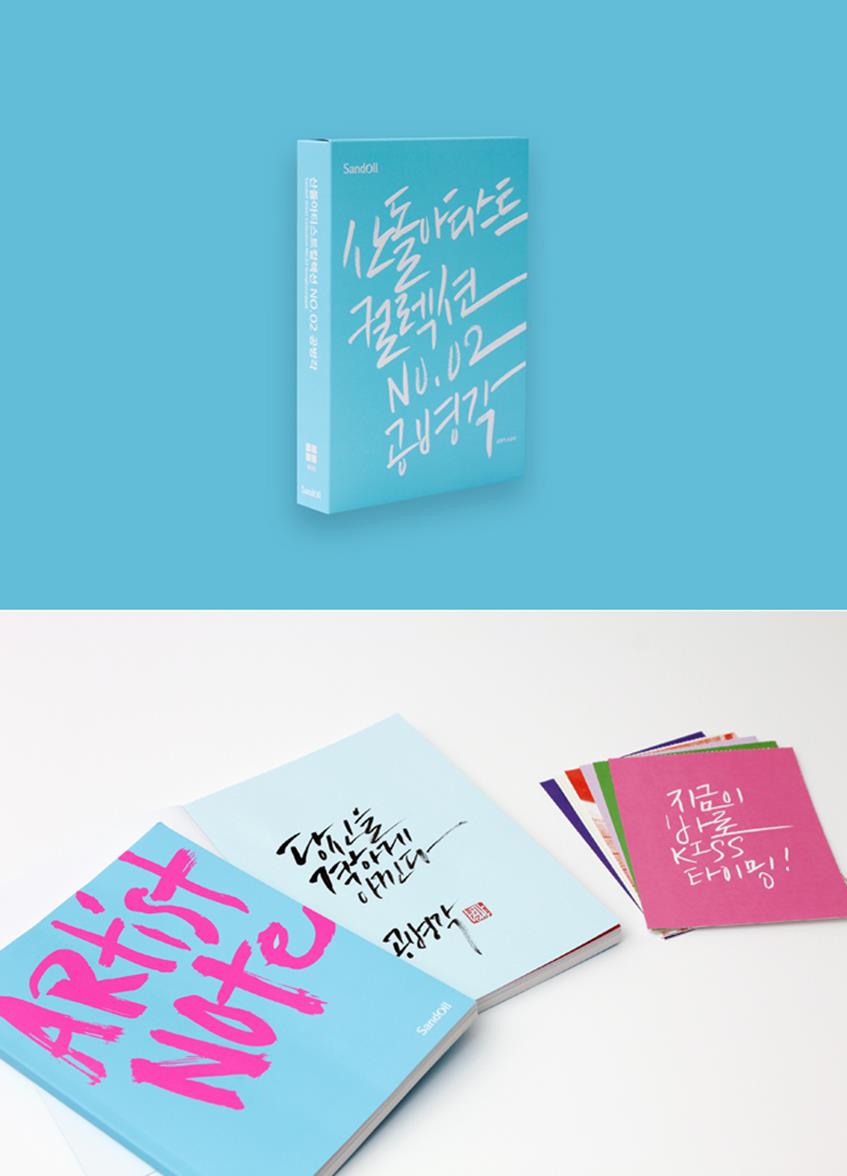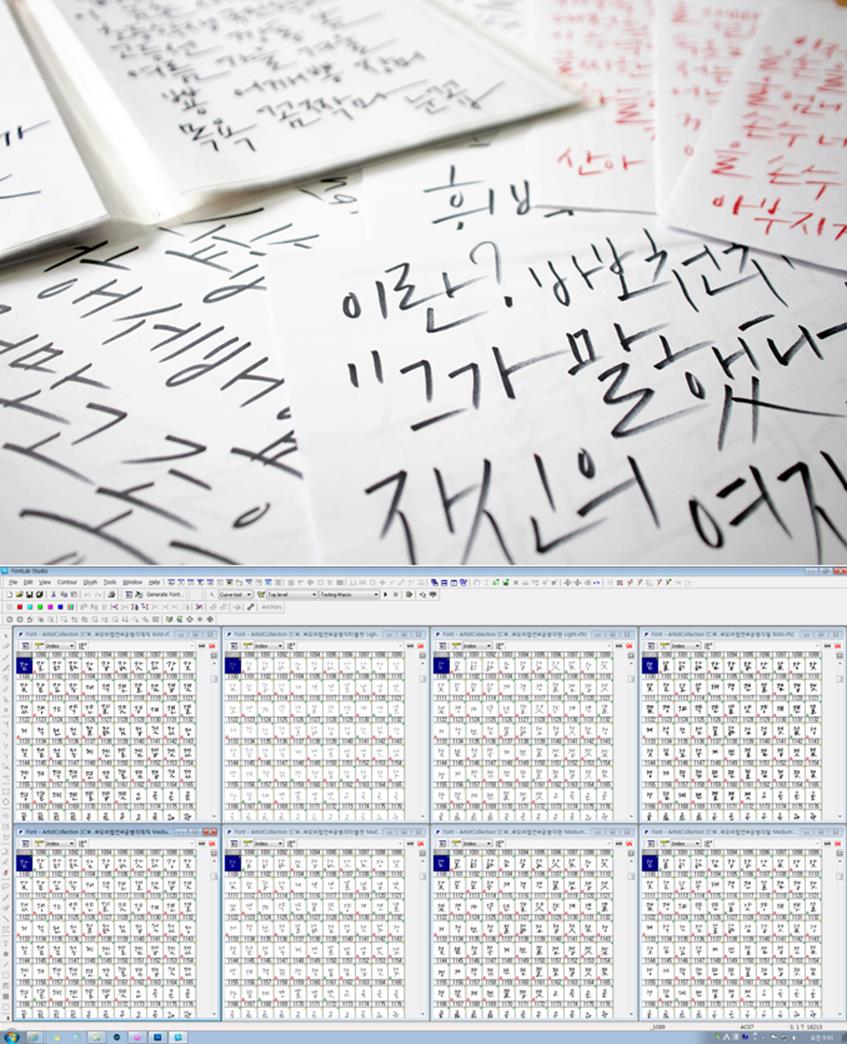
손이 행복해 삶이 즐거운 캘리그라퍼, 공병각
한 번 들으면 잊을 수 없는 이름. 한 번 보면 쉽게 잊을 수 없는 손글씨. 디자이너이자 크리에이티브 디렉터, 그리고 시선과 마음을 사로잡는 감성적 손글씨로 널리 알려진 캘리그래퍼 공병각을 만났다.
작가님 근황은 어떠신가요? 연초에 책 한 권을 내시고 6월 말에 또 한 권을 마무리하셨는데요.
네. 안녕하세요. 공병각입니다. 말씀대로 올해 2월에는 다섯 번째 에세이 <어떻게 사랑이 그래요>를 마무리해서 선보였고, 6월 말에는 제 첫 번째 손글씨 실용서라고 할 수 있는 <손글씨 잘 써서 좋겠다>를 출간했습니다. <손글씨 잘 써서 좋겠다>는 제가 작업했던 앨범 디자인과 기업 콜라보레이션 상품 작업 과정도 소개하고 제 경험과 노하우를 바탕으로 손글씨 쓰는 방법을 설명해주는 책이에요. 그동안 캘리그라피를 배우고 싶다는 문의와 어떻게 하면 손글씨를 잘 쓰는지 질문하는 분들이 굉장히 많았어요. 어떻게 하면 손글씨를 잘 쓰는지, 어떤 도구를 사용하면 좋은지 이제 답을 해줄 시점이 되었다는 생각으로 준비한 책이에요. 심혈을 기울였습니다.
이번 책도 작가님이 직접 디자인하셨나요?
이번에도 처음부터 끝까지 제가 글도 쓰고, 손글씨도 쓰고 사진도 찍고 디자인도 했어요. 출판사에서는 서너 명이 나눠서 하는 작업을 혼자 하다 보니 예상보다 출간 일정이 조금 늦어졌네요. 첫 번째 에세이는 제가 디자인하지 않고 제가 쓴 손글씨를 정리해 묶어 내는 형식으로 진행했어요. 그런데 제가 손글씨도 쓰고 디자인도 하고 있기 때문에 그 역량을 최대한 끄집어내자는 생각으로 그 이후에는 따로 맡기지 않고 직접 작업하고 있습니다. 제가 디자인해야 의도했던 손글씨 레이아웃을 온전히 표현할 수 있다고 생각해요. 초기 손글씨 에세이는 손글씨 위주의 손글씨가 부각되었어요. 그러다 점차 캘리그라피와 일러스트, 디자인, 사진 등의 소스들을 조화롭게 섞어가며 디자인하고 있어요. 캘리그라퍼가 만든 책보다는 캘리그라피 하는 디자이너의 책으로 다가갔으면 좋겠어요.
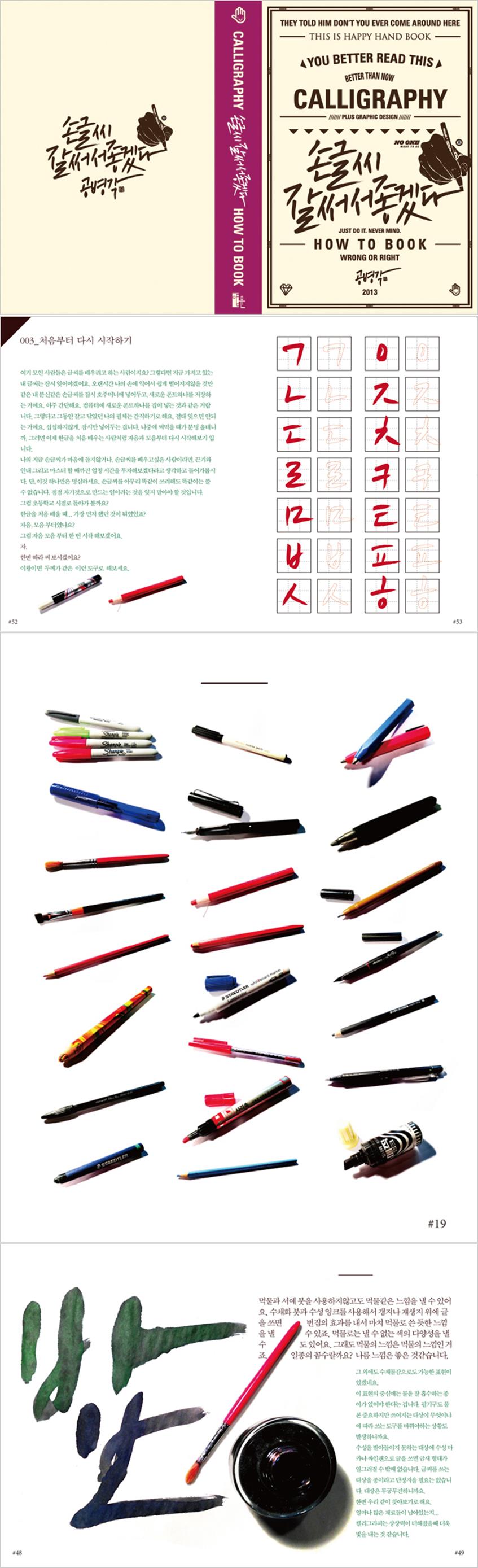
<손글씨 잘 써서 좋겠다> 표지와 본문 일부
책을 거의 매년 만들고 계신데요. 굉장히 사적인 ‘사랑’과 ‘이별’을 주제로 한 캘리그라피 에세이를 어떻게 시작하게 되었는지 궁금합니다.
첫 번째 책은 제가 기획하지 않았어요. 책을 쓰겠다는 생각으로 썼던 글씨들도 아니고요. 온라인에 올리던 제 글과 글씨를 좋게 봐주신 출판사 편집자분이 저를 설득해 첫 번째 에세이를 만들게 되었죠. (웃음) 누군가를 만나서 사랑하고 이별한 경험, 추억, 기억을 저는 사진보다는 손글씨로 남겼어요. 가까이 있는 펜으로 그때그때 제 감정을 제 손으로 솔직하게 썼죠. 그런 메모와 일기와 편지들이 쌓여있었고 그것들 중 일부를 출판사 권유로 스캔 받아 한 권의 책으로 묶어낸 것이죠. 사실, 책을 한 권 만들고 나면 그 책은 다시 보지 않아요. 다시 보는 게 부끄럽기도 하고 그때 감정이 증폭될 때도 있거든요. 어떤 부분은 설레지만 또 어떤 부분은 많이 아프죠. 전에도 말한 적이 있지만, 책을 쓰면서 다시 사랑하고 이별하는 느낌이에요. 그만큼 책을 만드는 일이 제게는 고통스러운 작업이기도 하죠.
유일하게 2012년도에는 책이 출간되지 않았던데요.
작년에는 거의 누워만 있었어요. 유난히 하고 싶은 일이 없었어요. 슬럼프, 침체기였던 셈이죠. 글도 쓰고 그림도 그리고 친구도 만나고 개인적인 기록과 활동은 꾸준히 했지만 외부 작업은 거의 하지 않았어요. 자전거 타고 한강도 가고 음악 많이 들으면서 사색하는 시간을 많이 가졌어요. 한동안 작업실에 갇혀 지냈어요. 그런데 올해 봄을 맞으면서 밖으로 많이 나오고 있어요. 작업실에서 잘 나오지 않고 어두울 때 작업이 더 잘 되는 사람으로 알고 있었는데 그런 것도 아니더라고요.
예전에는 비 오는 날이 좋았어요. 그런 날에 느껴지는 감성, 소리, 냄새들이 좋았는데 요즘은 햇볕이 너무 좋네요. 아는 분들은 알겠지만 집 앞에 놀이터가 있어요. 푸른 나무가 우거진 멋진 공간인데 거의 5년간 방치되어 있었죠. 최근에 그 공간을 정리해서 탁자와 의자도 놓고 친구들과 커피도 마시고 음식도 만들어 먹으면서 작업도 하고 있어요.
자전거 이야기도 잠깐 하셨는데요. 자가용을 처분하셨다면서요.
예전에는 비싼 자동차를 몰고 다녔어요. 겉멋이 들어있었죠. (웃음) 한동안 그런 허세를 버리지 못하고 있었는데 1년에 한 번씩 진행하고 있는 <나눔>이라는 자선바자회가 계기가 되었죠. 네 번째 <나눔> 행사를 진행해서 모은 기부금을 전해주고 동료들과 돌아오는 길에 자동차 사고가 났어요. 기부한 액수가 1,000만원 정도 되었는데 제 차 수리비가 1,500만원 가까이 나오더군요. 다행히 교통사고로 아무도 다치진 않았지만, 아이러니하다는 생각을 하게 되었죠. 누군가를 돕고 싶어 많은 사람이 열심히 준비해서 모은 돈보다 사고차량 수리비가 더 큰 상황이 아이러니하게 다가왔어요. 충격이었죠. 그 일을 계기로 차를 팔았어요. 많이 돌아다니는 편이 아니어서 최대한 걷고 대중교통을 이용하고 자전거를 타고 있습니다. 지금이 더 좋아요.
자전거가 놓여있는 작업실 분위기가 남다릅니다. 이 공간도 소개해주세요.
처음에는 집과 작업실을 분리했어요. 이 공간은 직원들과 함께 사용하는 작업실로 꾸미고 제 주거 공간은 따로 마련해서 오고 갔죠. 재미있는 공간을 만들고 싶었어요. 초기에는 프로젝터를 설치해 일하다 영화를 보거나 게임도 하고, 직원들과 자유롭게 작업할 수 있는 공간을 만들어보려고 했죠. DJ박스도 있었어요. 개인적으로 앤디워홀을 좋아하는데, 그가 운영했던 ‘더 팩토리(The Factory)’ 같은 느낌의 스튜디오로 꾸미고 싶었죠. 그러다 개인 작가로 활동하면서 주거 공간과 작업실을 합치고 큰 책장으로 침실과 작업공간을 구분해 한 공간에서 작업하고 생활하고 있어요. 이것저것 모으는 취미가 있어서 공간이 처음보다 많이 어수선해졌지만, 골프연습장 아래 있는 공간이라 겨울에 많이 춥지도 않고 한적하고 바로 옆에 공원도 있어 잘 쓰고 있어요. 제발 나가달라고 하지 않는 이상 떠나긴 어려울 것 같습니다. (웃음)
작업실 벽면에 사진도 많이 보이는데요. 직접 찍으셨나요?
네. 제가 찍은 사진들이에요. 한때 필름카메라로 사진도 많이 찍었죠. 최근에는 거의 대부분 아이폰으로 찍고 있어요. <손글씨 잘 써서 좋겠다>에 들어간 이미지들도 아이폰으로 촬영해 살짝 후보정한 사진들이에요. 아이폰 사진으로도 인쇄가 가능해졌네요. 최근에는 음식 사진을 많이 찍고 있어요. 제가 맛집도 굉장히 많이 알고 있거든요. (웃음)
남산 아래 위치한 공병각 작가의 공간
맛집이요?
네. 요즘 시장에 빠져있어요. 특히 광장시장은 꽉 잡고 있죠. 예전에는 샴페인이나 와인 마시고 데이트 하려면 청담동이나 압구정에 가야 한다고 생각했는데 나이 들면서 부질 없어 보이더라고요. 시장 음식이 더 맛있어요. 을지로, 종로에 있는 30년, 40년 전통의 음식들 먹어보면 기가 막힙니다. 친구들과 광장시장에 가면 한끼에 서너 군데 식당을 돌아요. 처음에는 마약김밥을 먹죠. 그리고 칼국수를 먹어요. 여러 집들 중에 꼭 가는 집이 있어요. 그리고 막걸리와 함께 순이네 빈대떡을 먹죠. 그리고 대구탕으로 마무리해요. 이젠 제 주변 사람들이 대부분 그렇게 다녀요. 먹는 것만큼 요리도 굉장히 좋아해서 요리책도 내보고 싶긴 해요.
손글씨, 그림, 디자인 그리고 요리까지. 작가님을 대표하는 키워드하면 ‘손’이 될 것 같은데요. 언제부터 ‘손재주’가 있었는지 궁금합니다.
언제부터였다고 말하긴 어렵지만 어려서부터 내성적인 성격이라 밖에서 뛰어놀기 보다는 집안에서 블록 만들고 장난감도 조립하고 그림 그리는 시간을 즐기긴 했어요. 그런 시간들이 어쩌면 제 삶에 영향을 주었을지도 모르죠. 그림 그리길 좋아하긴 했지만 처음부터 글씨를 잘 쓰진 못했어요. 돌이켜보면 글씨 잘 쓰는 누나 영향으로 예쁘게 글씨 쓰는 연습을 하면서 손글씨에 관심을 갖게 된 것 같아요.
본격적으로 손글씨 작업을 시작하게 된 계기가 있나요?
20대 초반부터 광고 일을 했는데, 본격적인 손글씨 작업은 디자이너 막내로 있을 때 맡았던 스타벅스 지면 광고 프로젝트가 계기가 되었어요. 어떻게 광고하면 좋은지 아이디어를 내놓으라는 지시가 저를 포함한 몇 명의 디자이너에게 주어졌고 잘 해보고 싶은 마음에 밤 늦도록 그림도 그려보고 이런저런 글씨를 써보면서 시안을 만들었어요. 운이 좋게 제 시안이 채택되었고 제 손글씨가 처음으로 지면 광고로 선보였죠. 그 이후로 저만의 손글씨 스타일을 만들기 위해 꾸준히 연습하고 다양한 도구를 활용해 실험도 많이 했죠. 최근에는 먹과 붓을 이용해 손글씨를 많이 쓰고 있어요. 붓글씨는 오래 전에도 해봤지만 잘 맞지 않는 것 같아 잊고 있다가 다시 붓을 잡았죠. 이젠 어느 정도 안정된 느낌이에요. 제 2의 손글씨 도구가 될 것 같아요. 붓글씨 스타일도 폰트로 만들어보고 싶어요.
주로 어떤 도구들을 사용하시나요?
이번에 <손글씨 잘 써서 좋겠다>는 책을 만들면서 제가 사용했던 도구들을 나열해봤는데 100개도 넘더군요. 그 중에 저랑 궁합이 맞는 것만 추려보니 20개 정도 되네요. 가장 많이 사용하는 필기구는 축지색연필(종이말이 색연필)이고 매직마카, 앞서 얘기한 붓 정도에요. 많은 필기구와 종이를 사용하고 있지만 각각의 프로젝트에 맞는 재료를 골라서 작업하고 있어요. 최근에는 붓을 사용하면서 글씨체가 또 달라졌어요.
팬시 브랜드를 준비 중이라고 들었습니다.
책을 마무리하고 그 작업을 진행하고 있어요. 글씨를 쓰고 손글씨에 대한 이야기를 많이 하게 되면서 글씨 쓰는 일은 ‘손’이 즐거운 작업이라는 생각이 들었죠. 글씨가 써지는 질감을 느끼면서 머리 속에 생각했던 글씨가 써졌을 때의 즐거움이 크거든요. 제 손을 움직여 만드는 작품이잖아요. 그래서 ‘해피핸드(Happy Hand)’라는 브랜드를 런칭할 계획이에요. 손이 즐겁게 해주는 아이템들은 뭘까 생각하면서 평소에 자주 사용하는 다이어리, 노트, 필기구 등의 쓰임새를 조금 더 고민해서 만들어보면 어떨까 한 것이죠. 글씨를 가르쳐주는 책을 마무리 했으니, 다음에는 “이런 도구를 사용해보는 건 어때?” 하면서 제안하는 거에요. 그 동안 책이나 인쇄물, 광고 등을 통해 제 손글씨를 접했다면 매장에서 보게 될 수도 있습니다. 제 손글씨가 입거나 쓸 수 있는 오브제로도 재탄생할 것 같아요. 기대해주세요.
토크쇼 형식으로 진행된 9차 폰트클럽 세미나 <공병각 토크쇼, 감성 손잡기>에서 손글씨를 시연하고 팬들과 이야기를 나눈 공병각 작가.
마지막으로, 계획이 있으면 얘기해주세요.
앞서 말씀 드렸던 <나눔>이라는 행사는 죽을 때까지 해볼 생각입니다. 수익금은 모두 도움이 필요한 분들에게 전달됩니다. 재능을 나누고 싶은 분들은 언제든지 연락 주세요. 손글씨 강연에 대한 문의도 많이 하시는데요. 몇 번 초대를 받아 특강을 해보긴 했지만 캘리그라피라는 분야가 하루에 몇 시간 가르쳐드린다고 기대한만큼 얻어갈 수 있는 영역이 아니기 때문에 다른 방법을 생각해보고 있어요. 언제가 될진 모르지만 기회가 되면 커리큘럼을 짜서 며칠간 손글씨를 가르쳐드릴 수 있는 시간을 가져볼까 합니다. 제 그림과 글씨를 포함해 그간의 작업들을 정리하는 전시도 생각해보고 있어요. 장기적으로는 계획을 계속 만드는 게 제 꿈이에요. 멈추지 않고 새로운 일들을 계획하고 실행해나가고 싶어요. 계속 뭔가 궁금해하고 도전하면서 살면 좋겠어요.